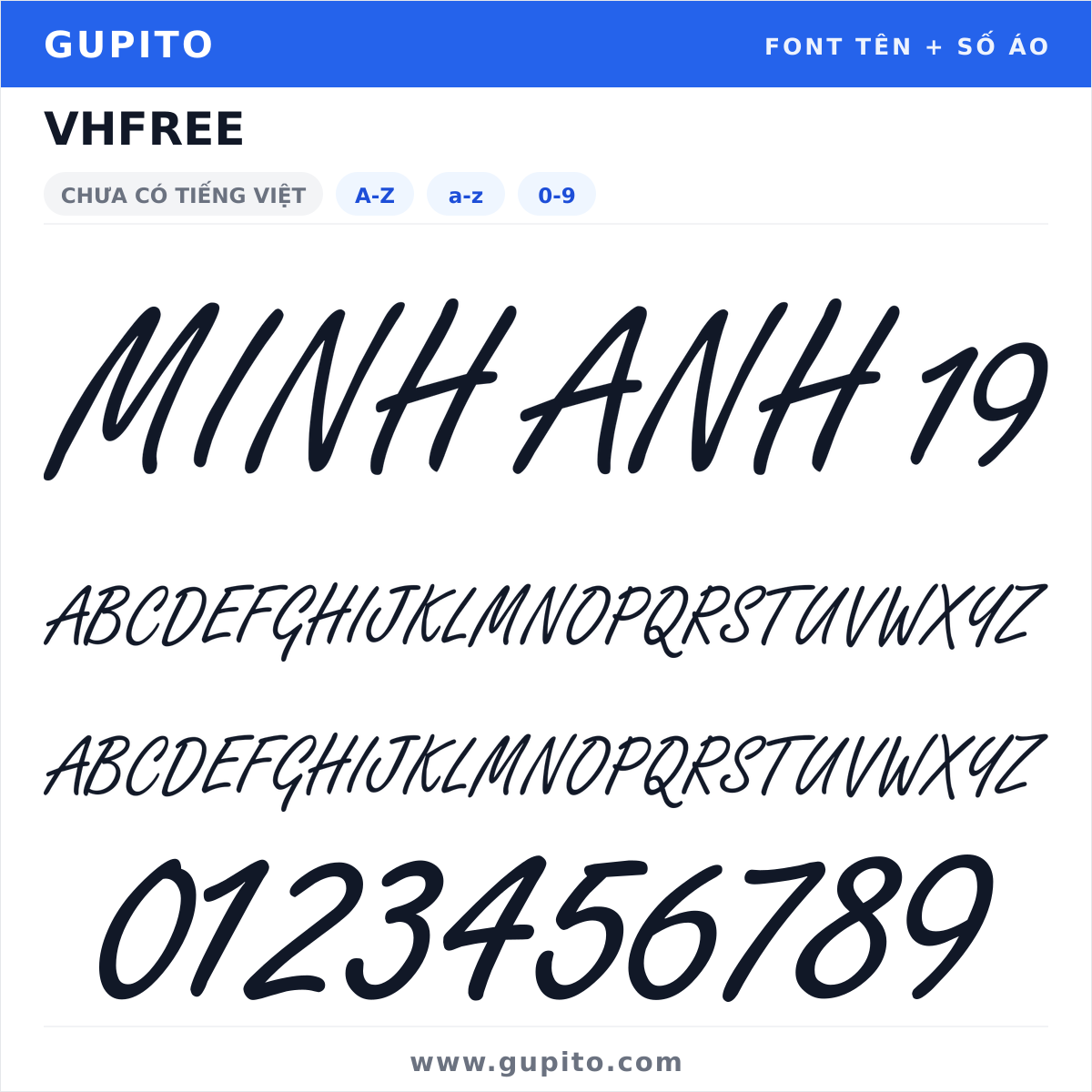
.VnFreeH Medium
.VnFreeH Medium · Font VHFREE in tên áo, số áo bóng đá, chữ ký · chữ ký, nghiêng, mềm mại
Font VHFREE với nét chữ ký độc đáo, thích hợp in tên, số áo bóng đá, áo lớp, quà tặng. Có bảng số 0-9. Bộ chữ .VnFreeH Medium dùng để in chuyển nhiệt lên áo đấu, áo lớp, áo nhóm và đồ thể thao theo yêu cầu. Kiểu dáng: chữ ký, nghiêng, mềm mại. Font dùng cho chữ không dấu và số áo. Có đủ bộ chữ số để in số áo. Từ khoá liên quan: font vhfree, font in ten ao, font in so ao, font chu ky, font the thao, font bong da, font a-z, font 0-9.